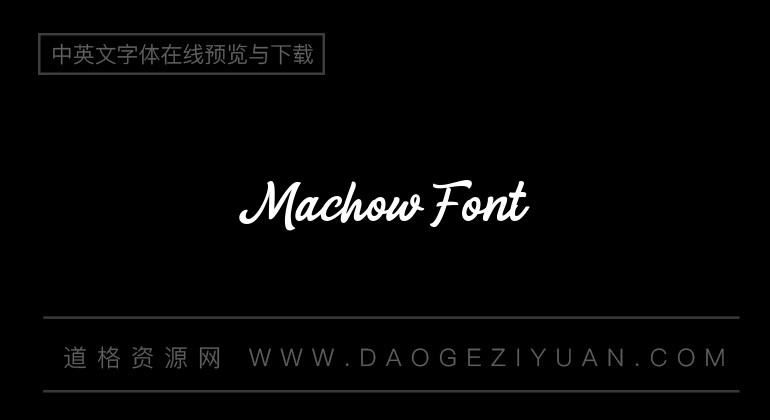
Machow Font(马超字体)是一种具有独特风格的中文字体,由中国设计师马超创作。该字体结合了传统的毛笔书法和现代平面设计元素,呈现出一种兼具传统与现代美学的风格。 Machow Font 字体的特点之一是其极简主义的设计风格,简洁而不失优雅。其字形线条流畅,具有一定的笔画变化,同时字体整体风格稳重而富有力量感。该字体适用于多种场合,如书籍、海报、品牌商标等。 此外,Machow Font 字体还具有多种字重可供选择,包括常规、细体、粗体、黑体等,可以满足不同设计需求。内容介绍
Machow Font是一款非常不错的手写艺术字体,具有很好的视觉感,适合于文化类的宣传设计、商业类品牌的广告和产品包装设计以及个性化文字排版等较多场景。